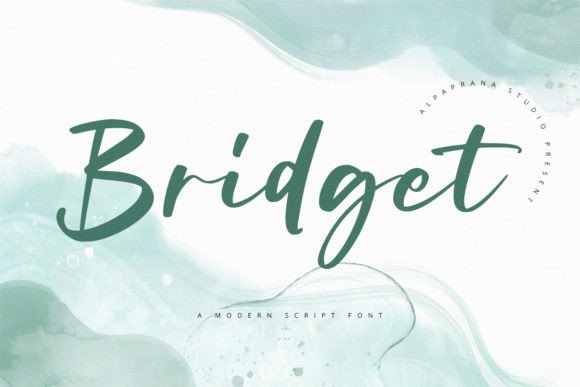
Bridget
Bridget Script: A Fonte que Une Modernidade e Elegância Clássica
Se você está em busca de uma tipografia que combine o charme atemporal com um toque contemporâneo, Bridget Script é a escolha ideal. Desenvolvida para ser versátil e impactante, ela traz uma sensação natural que se destaca em qualquer aplicação de design.
Por que escolher Bridget Script?
- Estilo único: linhas fluidas e curvas suaves que lembram a caligrafia manual, proporcionando um visual premium.
- Alta legibilidade: mesmo em tamanhos menores, a fonte mantém clareza, ideal para branding e materiais impressos.
- Versatilidade total: perfeita para logos, etiquetas de roupa, capas de livros, pôsteres, embalagens, sacolas de compras, camisetas e muito mais.
- Impacto visual: cria uma identidade visual forte, ajudando a diferenciar sua marca da concorrência.
Aplicações recomendadas
Bridget Script brilha em diversas áreas. Veja onde ela pode transformar seu projeto:
- Branding e identidade visual de empresas
- Logotipos e logotipos tipográficos
- Design de roupas e etiquetas de moda
- Pôsteres de eventos e campanhas promocionais
- Capas de livros e revistas
- Embalagens de produtos premium
- Sacolas de compras e materiais de ponto de venda
- Camisas, camisetas e mercadorias personalizadas
- Fotografia e projetos de arte editorial
Em resumo, Bridget Script oferece uma combinação rara de sofisticação clássica e modernidade, tornando‑a indispensável para designers que desejam criar projetos memoráveis e de alto impacto. Experimente hoje e veja como essa fonte pode elevar a identidade visual da sua marca a um novo patamar.